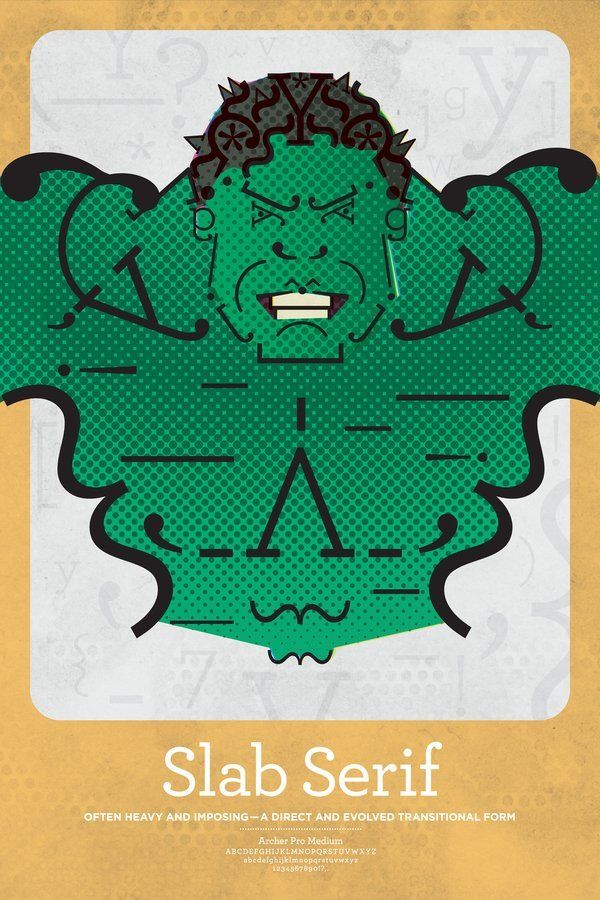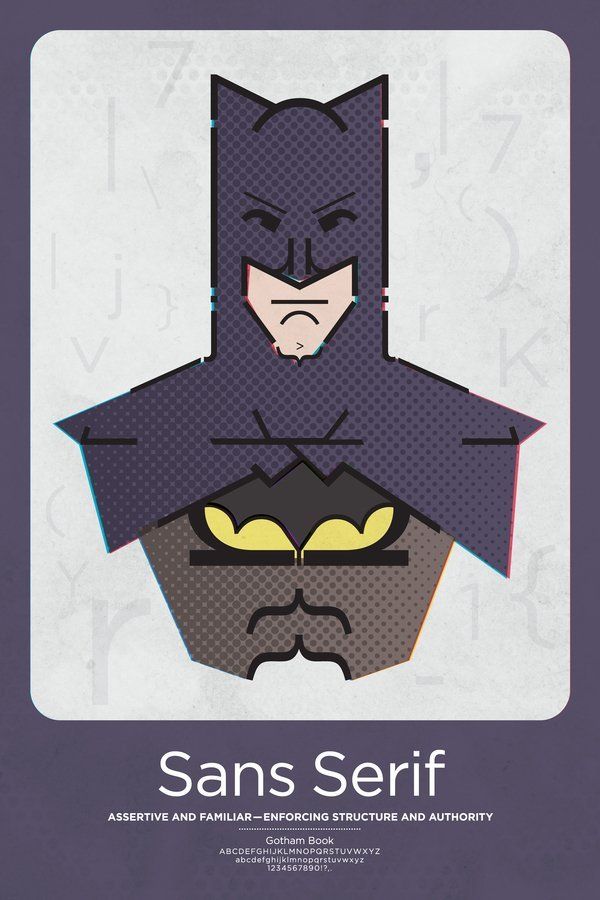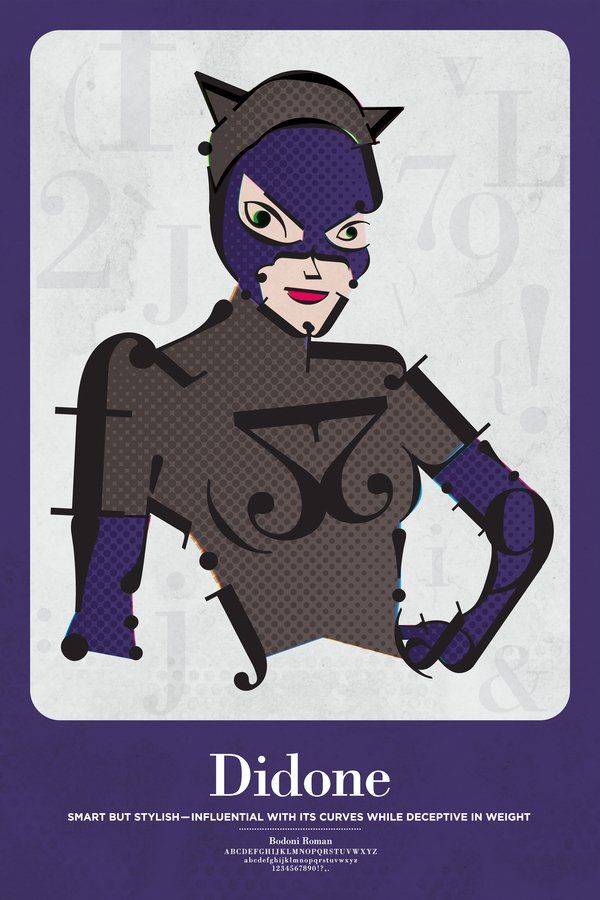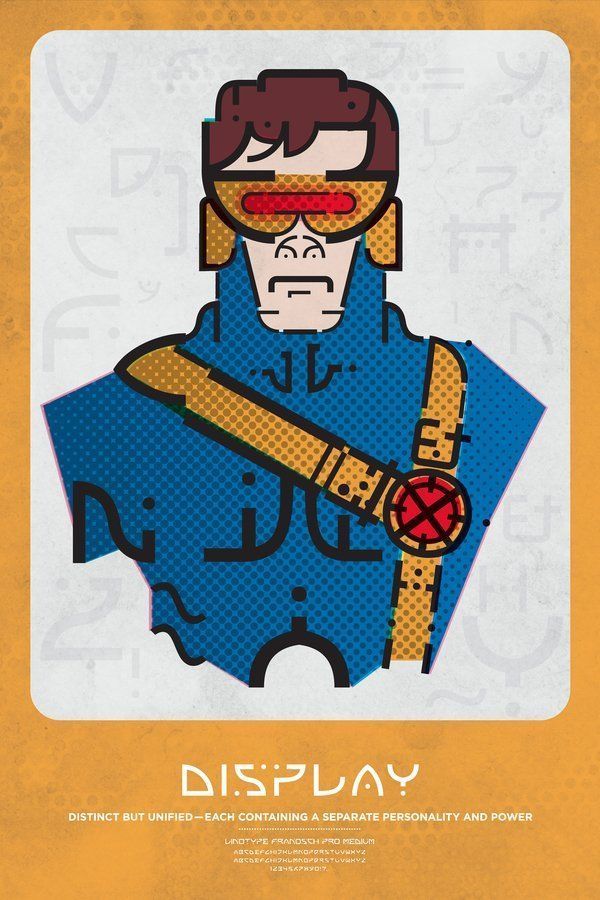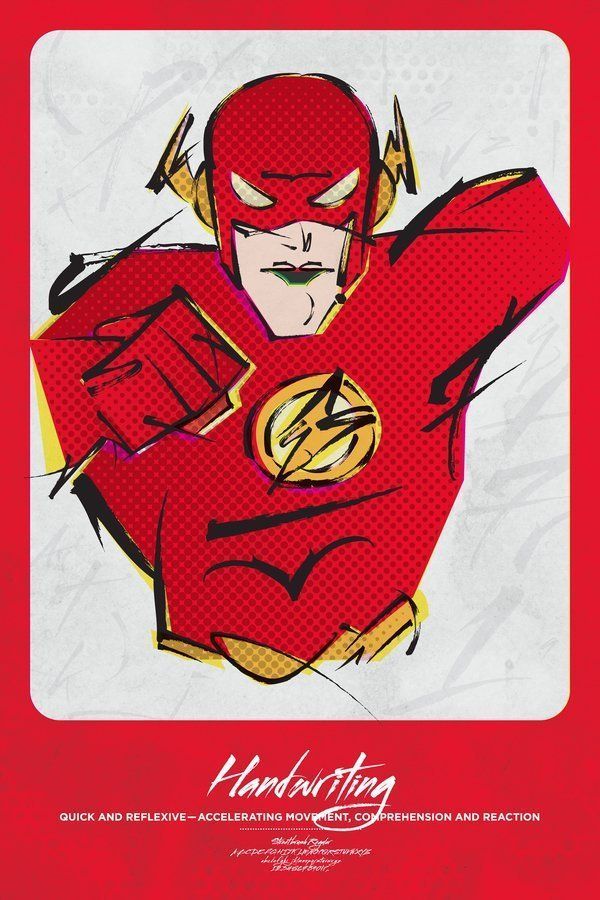
in Design, Super-héros Si les Super-héros étaient des polices de caractère par Mr Geek 25 juillet 2012, 12:00mis à jour le 7 août 2024, 19:57 Le designer américain Matthew Olin s’est lancé dans une petite expérience consistant à associer à 8 super héros une police de caractères qui leur ressemble. Au programme : Batman, Superman, Spider-Man, Hulk, Catwoman, Cyclope, Flash et Thor. Le résultat, plus scolaire que les portraits typographiques d’Aurélie Scour, vaut néanmoins le coup d’oeil : Source Behance Typographie Mr Geek Fan de comics et de gadgets depuis tout petit, je bidouille tout ce qui me passe entre les mains. Mes opinions n’engagent que moi. facebook twitter delicious linkedin